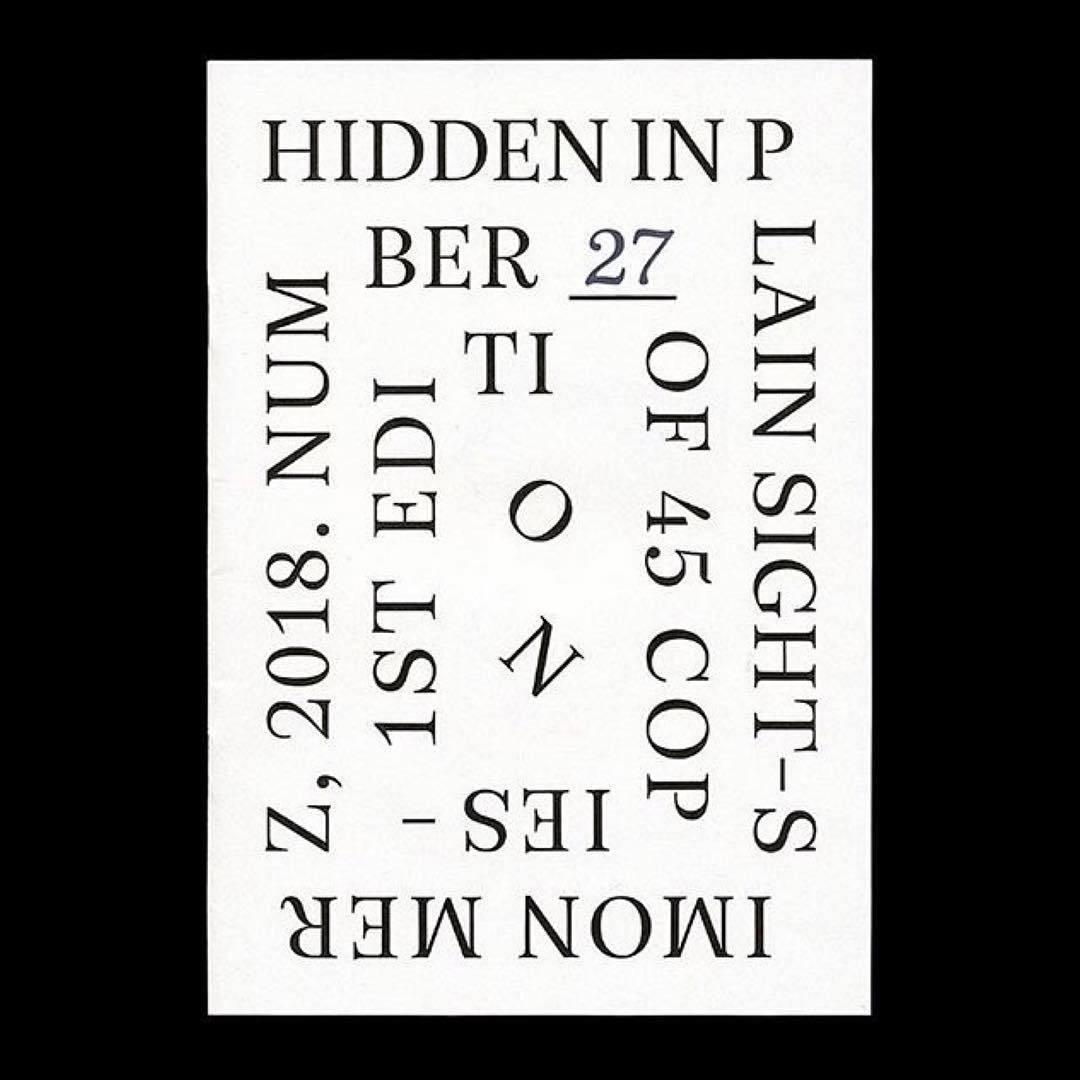
Welche (moderne?) schlichte Serifenschrift ist das
Hallo, ich in über einen Blog auf diese Schrift gestossen und habe leider keine Hintergrundinformationen dazu.
Hat jemand eine Idee, welche Schrift das sein könnte?
Das "R" hat mich an die Miller erinnert. Die ist es aber nicht.
Es wurden auf jeden Fall zwei verschiedene Schriften für den eigentlichen Text und die Nummerierung der Exemplare (in dem Fall Exemplar 27) verwendet. Zu sehen an den unterschiedlichen Formen der 2.